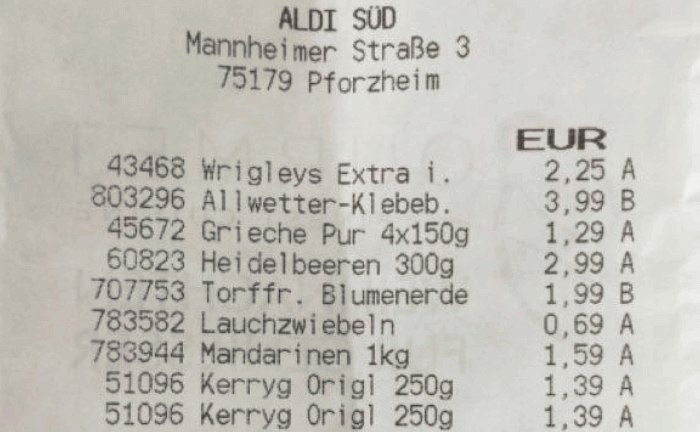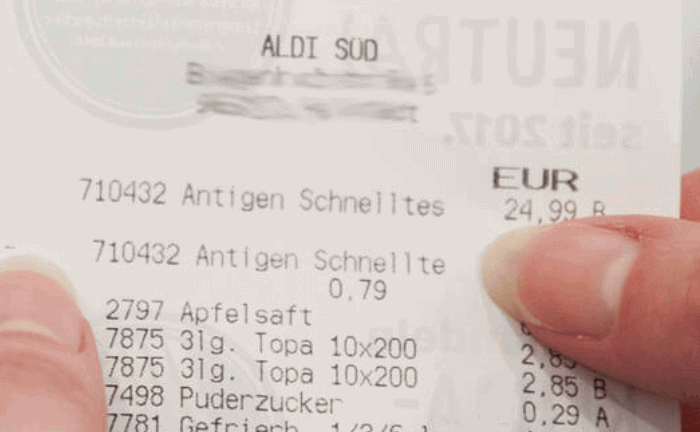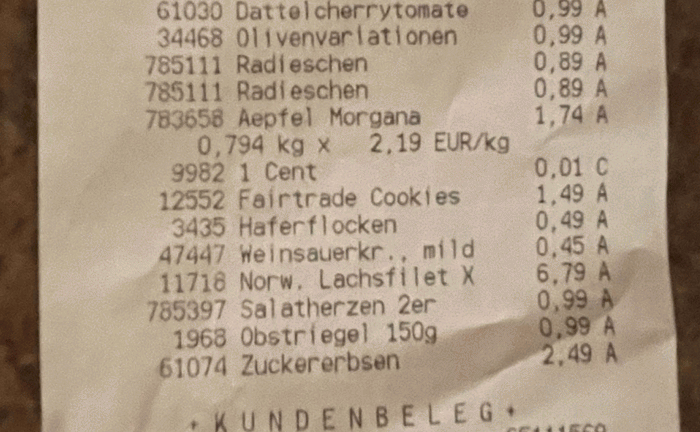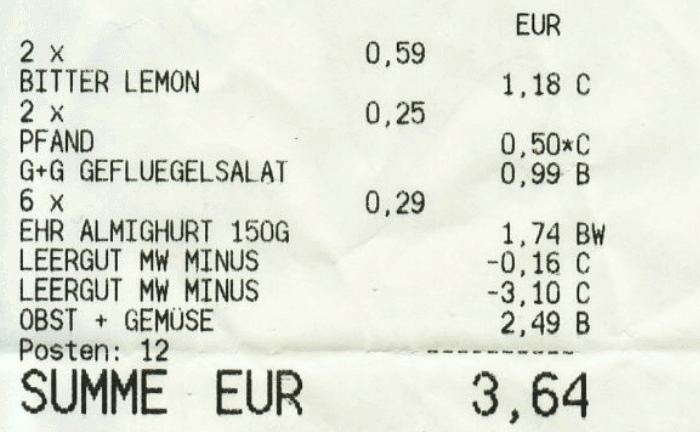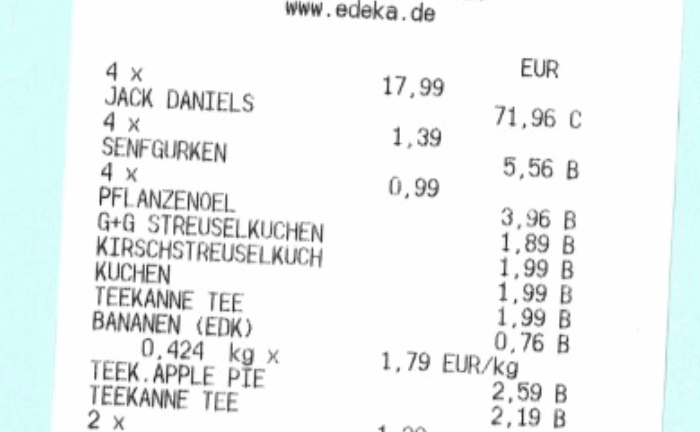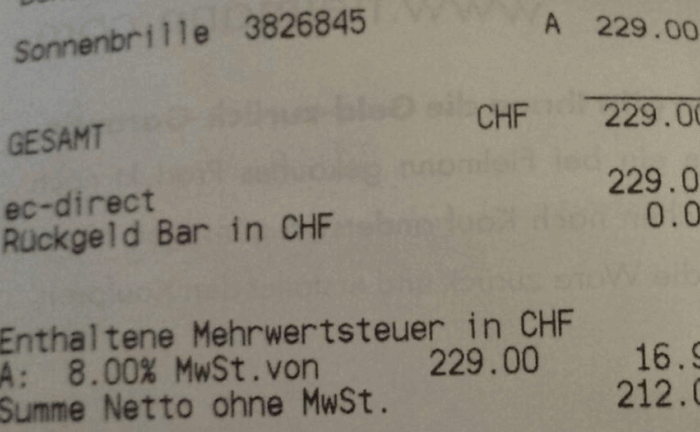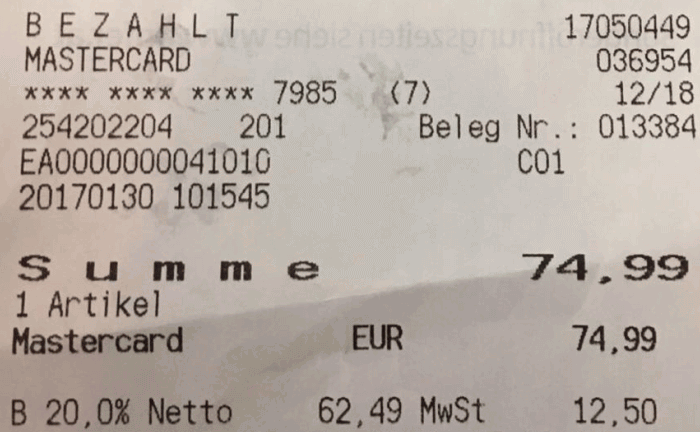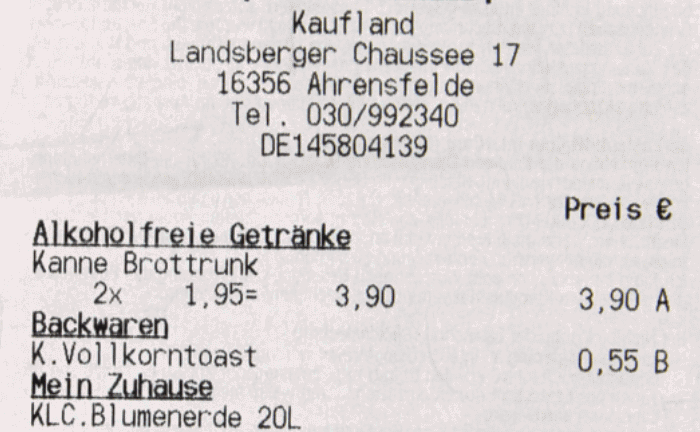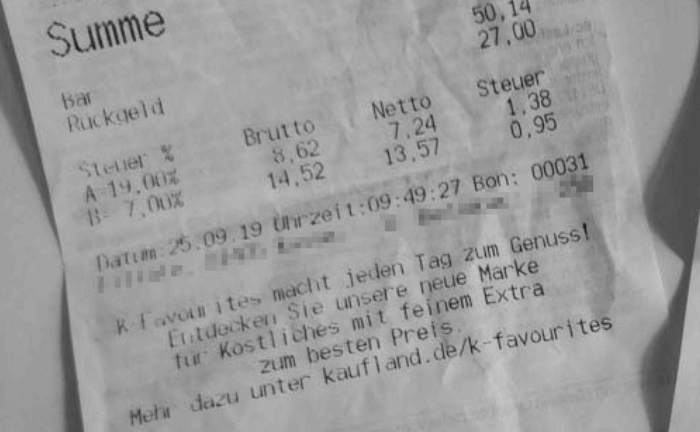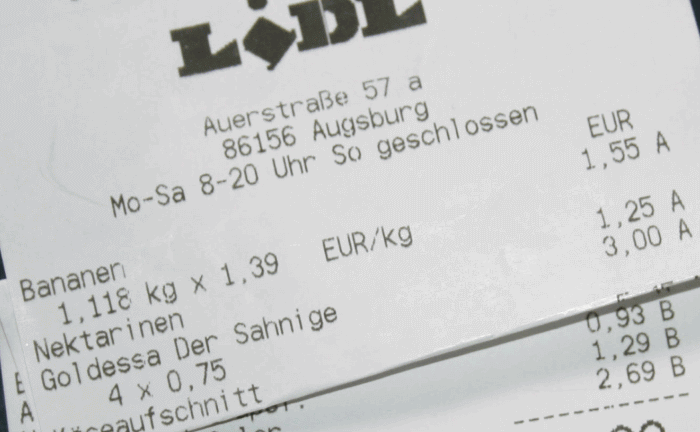
Eine der am häufigsten verwendeten Schriftarten auf Rechnungen in Supermärkten und Geschäften
wird häufig in Supermärkten wie ALDI, Edeka, Kaufland, Hofer, fielmann, Lidl, Müller usw.
Eine der am häufigsten verwendeten Schriftarten auf Quittungen in Supermärkten und Geschäften
auf dem Computerbildschirm angezeigt
gedrucktes Sample von der Schriftart